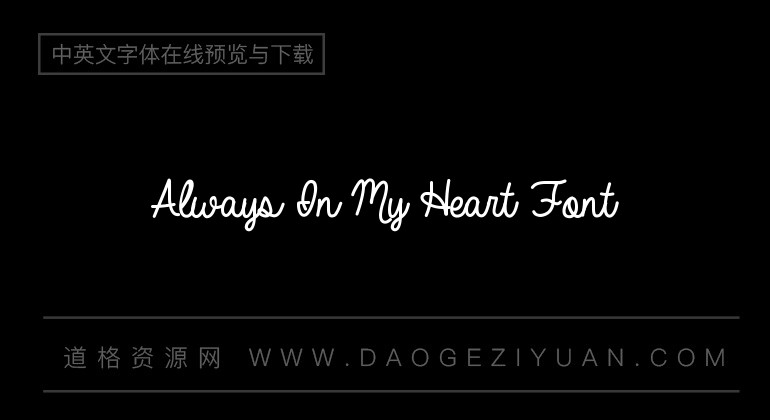
Always In My Heart Font
Always In My Heart Font 是一种优美的手写字体,它特别适合用于情感、感恩、纪念等场合。这种字体的字母形状流畅、有点带有几分草书的感觉,字母之间的间距较小,整个字体看起来比较紧密。同时,这种字体有着浓郁的个性化和温馨感,适合用于卡片、海报、宣传册等设计中,增强设计作品的感染力和亲近感。
Always In My Heart Font是一款非常不错的手写艺术字体,具有很好的视觉感,适合于文化类的宣传设计、商业类品牌的广告和产品包装设计以及个性化文字排版等较多场景。